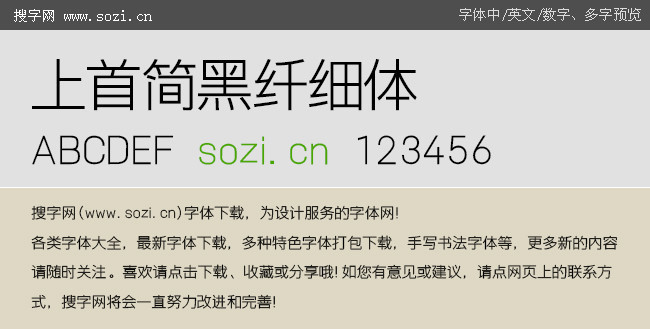
上首簡黑纖細(xì)體
搜字網(wǎng)給大家提供一款上首簡黑纖細(xì)體中文字體下載,上首簡黑纖細(xì)體字形方正,風(fēng)格簡約,重心平穩(wěn),筆畫極細(xì),給人以平和的感覺,筆劃整齊劃一。適用于搭配標(biāo)志、廣告標(biāo)語、商業(yè)廣告等廣告設(shè)計(jì)。